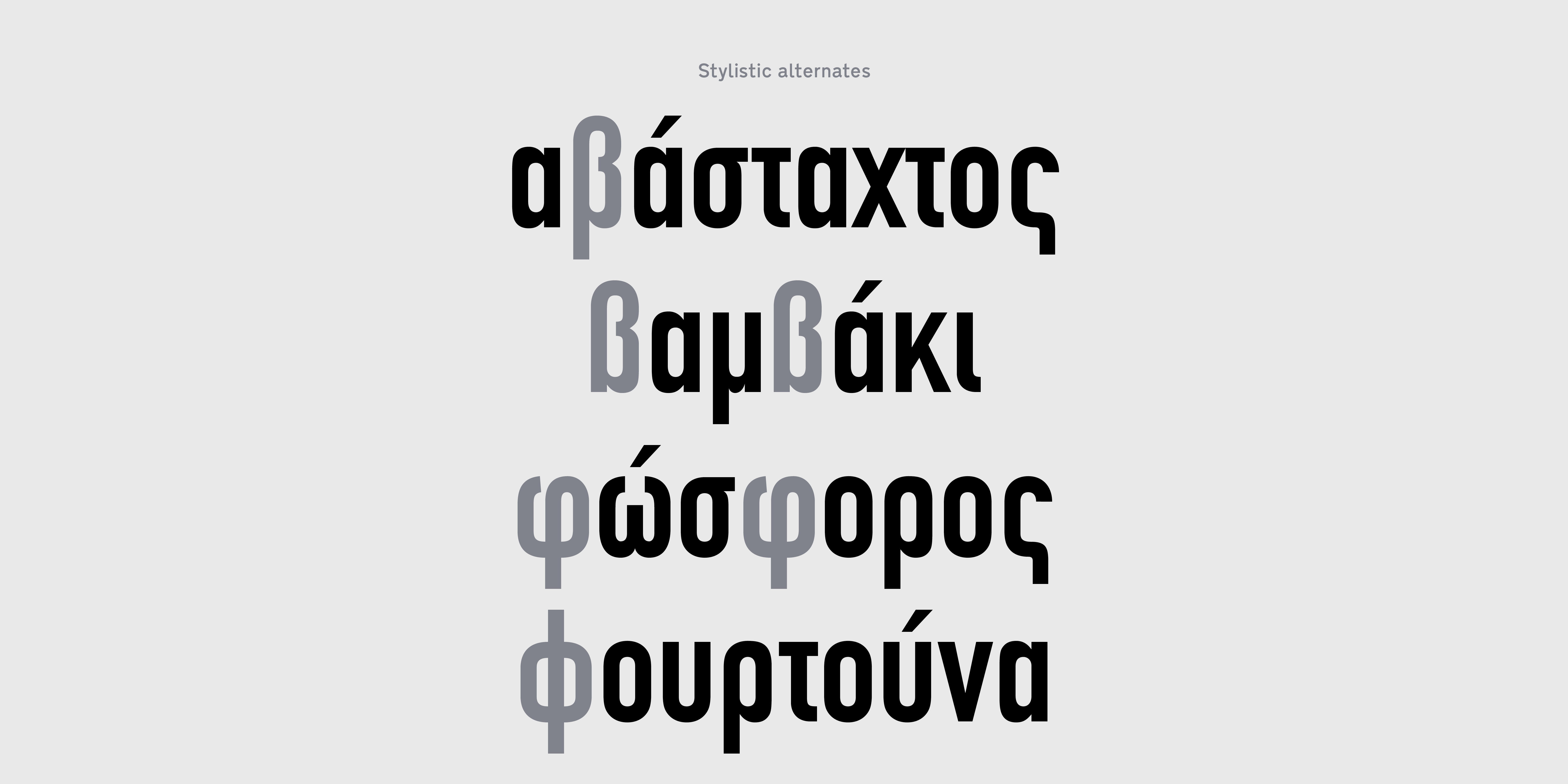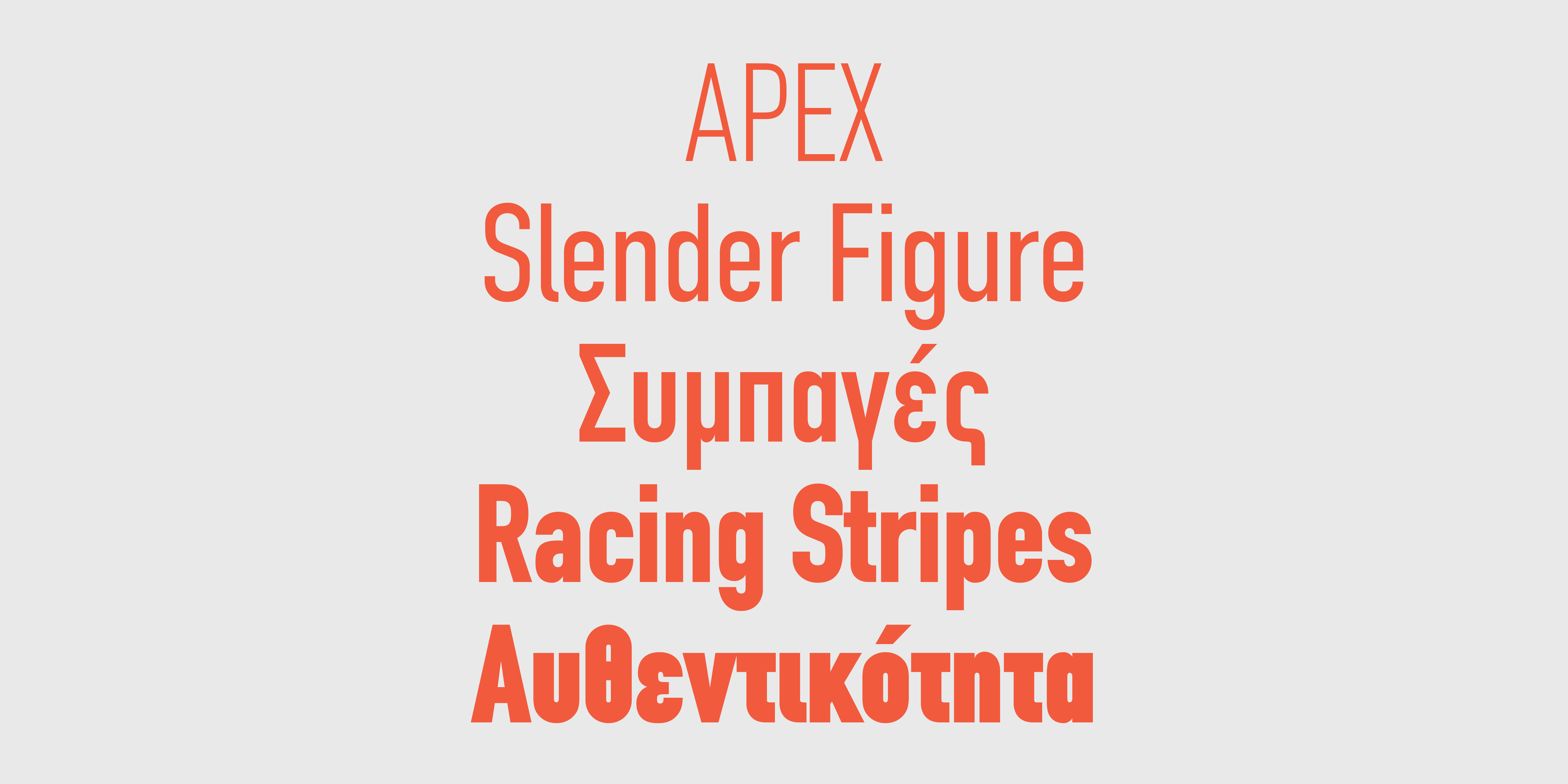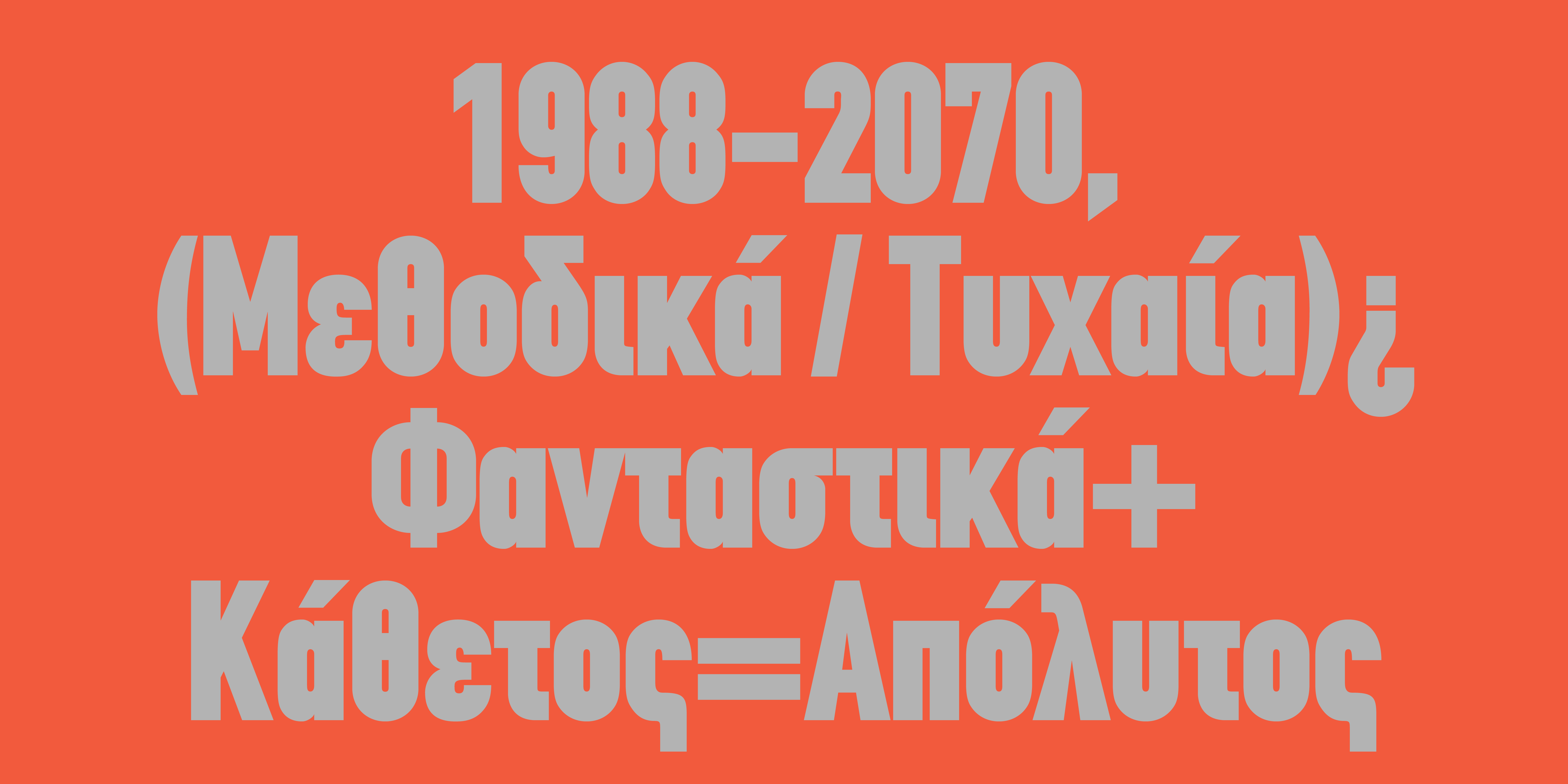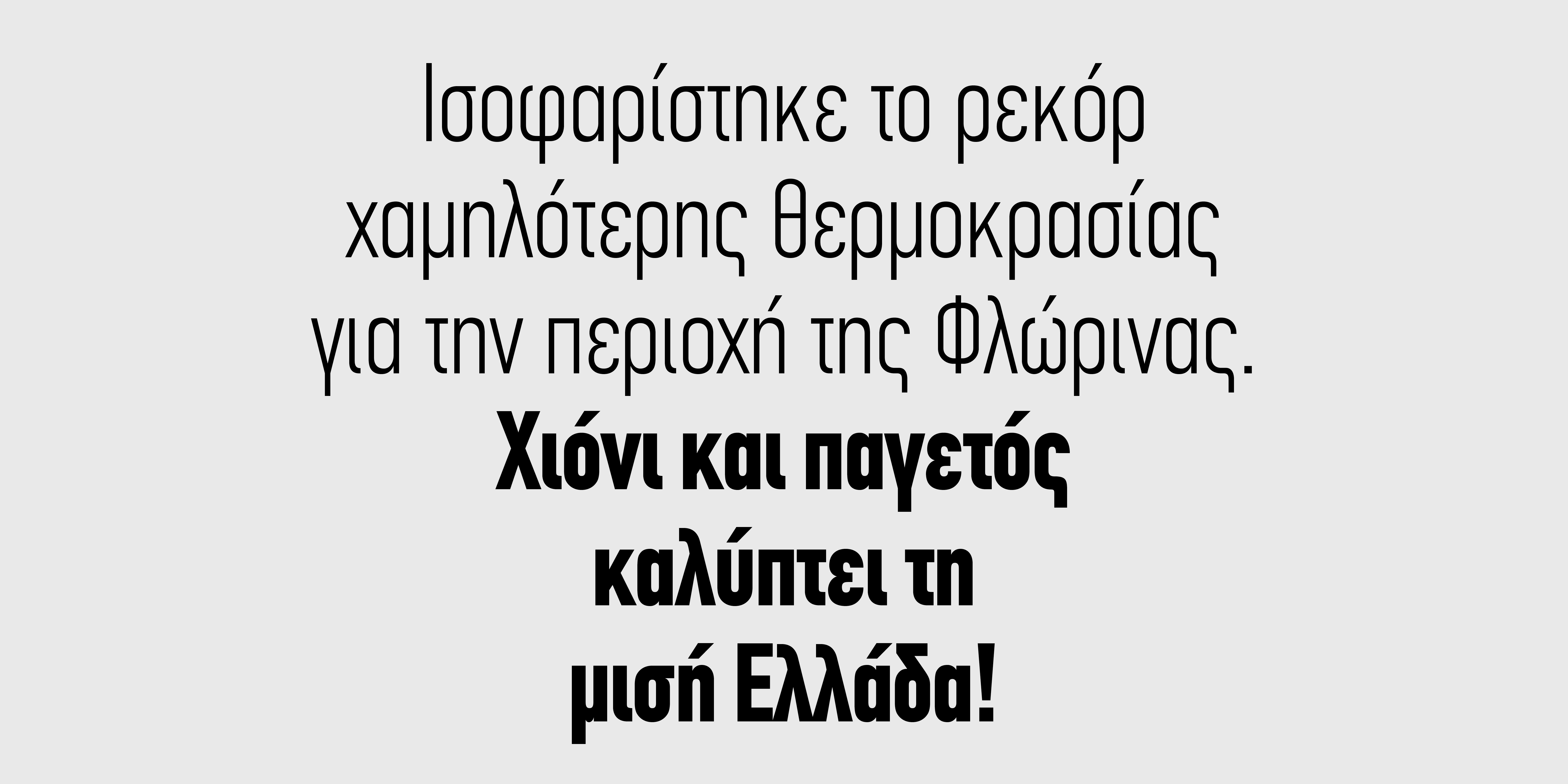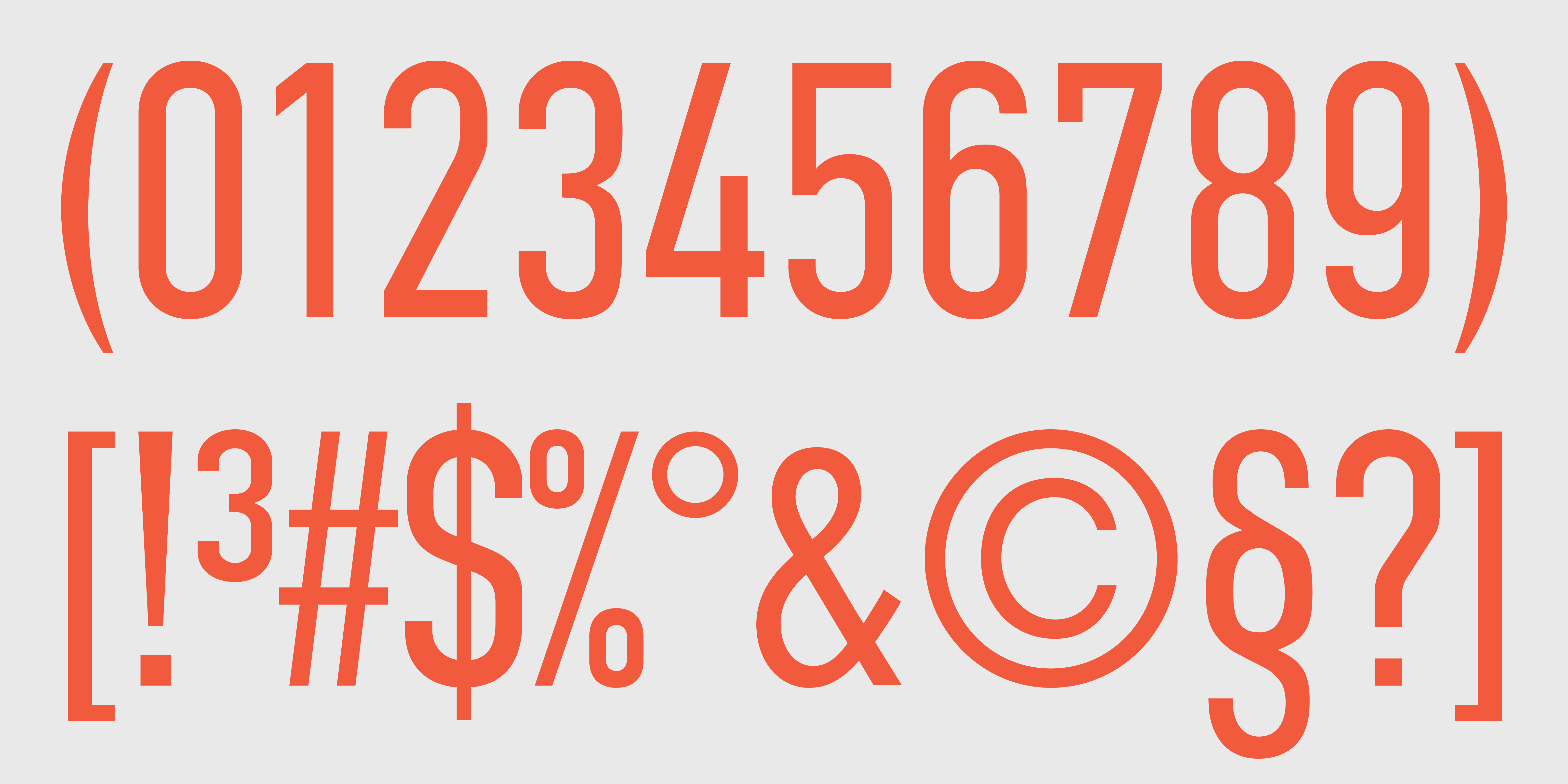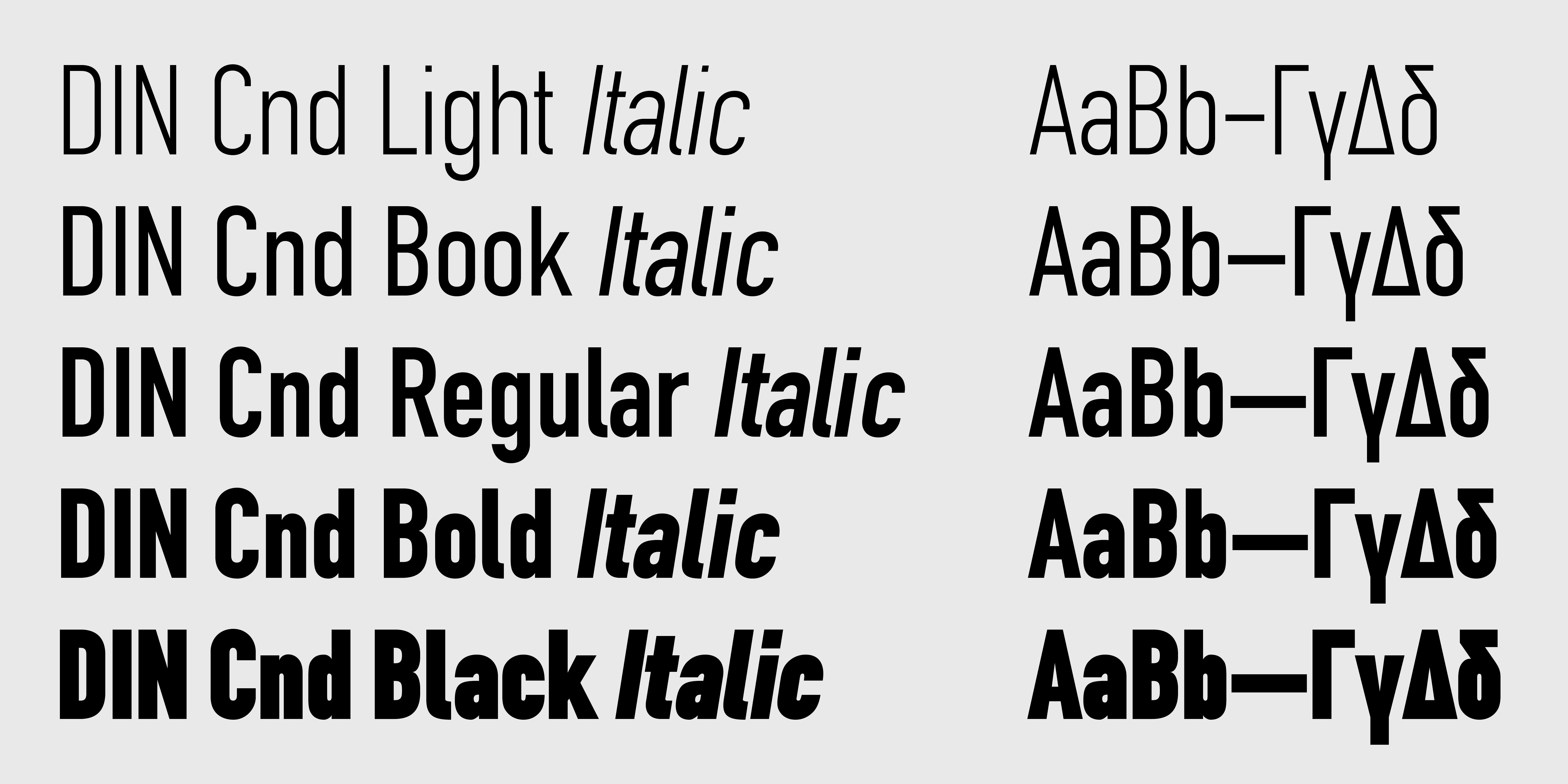
DIN CF Cnd
Σχεδιάστηκε αρχικά ως εταιρική γραμματοσειρά εταιρίας τηλεφωνίας αν και μία παραλλαγή της χρησιμοποιείται για τη σήμανση των Ελληνικών Αυτοκινητοδρόμων. Η νέα έκδοση Std (2012); έχει επανασχεδιαστεί, έχουν προστεθεί νέα βάρη, πλάγιοι χαρακτήρες, ανισοϋψής και σταθερού πλάτους αρίθμηση, κλάσματα, ενώ εκτός από Ελληνικά η Std έκδοση υποστηρίζει Western, Turkish & Romanian character sets.